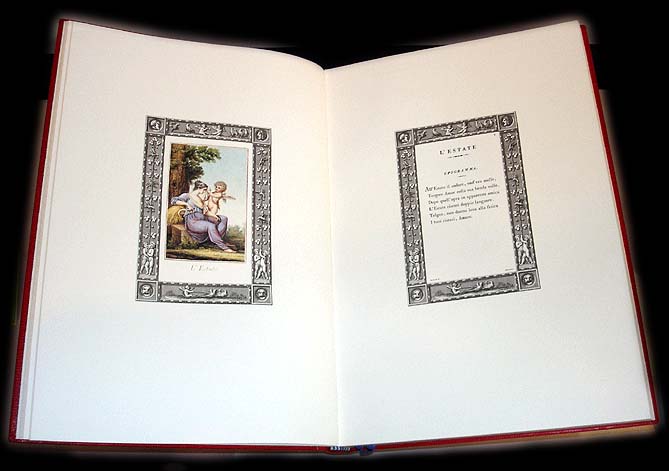
A letra neo-classicista de Bodoni
A mais «clássica» e pomposa letra de sempre — o excepcional desenho do mestre tipógrafo italiano. Os tipos Bodoni foram o resultado de 250 anos de evolução no design do tipo romano: linhas finas e subtis contrastam fortemente com hastes mais pesadas.
Os caractéres de Giambattista Bodoni também são determinados pelo seu forte acento vertical.
"Os caracteres criados por Bodoni caracterizam-se agora sobretudo pela passagem subtil e cuidadosamente estudada do traço fino ao traço grosso ou pela coexistência de hastes finas e grossas, num jogo de claro escuro que é também o jogo em que é baseada a página bodoniana.
Com uma alternância estudada do corpo da letra nas linhas dos títulos e um cuidado especial na escolha dos papeis e das tintas, a página é ampla, simples, com margens e espaçamentos entre linhas generosos e grandes áreas da página em branco.
A procura de clareza e luminosidade da página é reforçada pelo uso de tipos com altura-x reduzida e longos ascendentes e descendentes. Esta dialéctica do branco e negro dos caracteres é já, claramente, neo-clássica."
(Da apresentação de João Bicker à sua tradução do Manual Tipográfico de Giambattista Bodoni, Coimbra, Almedina, 2001, pg.38-39)
Torquato Tasso, Aminta, favola boschereccia, Parma 1789
As quatros fontes da beleza de um caractere, segundo Bodoni
«Dos quatro aspectos dos quais emana toda a beleza de um caractere, o primeiro é a regularidade. Analisando o alfabeto de qualquer idioma, vamos encontrar não só traços similares num grande número de letras distintas, mas também verificar que podem ser compostas de poucas partes idênticas, combinadas em grupos.
Se tomarmos a média de tudo – o que não serve para distinguir uma letra da outra –, e acentuarmos tão claramente quanto possível as dife­renças mais necessárias para esta distinção, conseguiremos fixar, para determinar a forma de todas as letras, uma ordem e uma regra; surge semelhança sem ambiguidade, variedade sem dissonância, igualdade e simetria sem confusão.
[...] Em segundo lugar vêm a nitidez e o polimento, oriundos da perfeição dos buris e da fundição perfeita dos caracteres. [...] A terceira condição é a escolha das melhores formas, em concordância com o bom gosto, com o espírito da nação e o espírito do século.
A moda reina na escrita como em todas as coisas, impon­do-lhe regras, razoáveis ou não. No entanto, se não houver nenhum motivo melhor e se a moda nos deixar livres, o bom gosto irá orientado pela simplicidade — não a simplicidade grosseira que se mani­festaria em traços uniformemente espessos, mas por uma simplicidade agradável e de boa qualidade, como a que observamos no harmonioso contraste de claro e escuro em todo a caligrafia feita com uma pena bem apontada e firme.
A graça é o quarto e último requisito para com­pletar a beleza do impresso. Sabemos quão difícil é explicar o que há de atraente, encantador e delicioso naquilo a que chamamos «graça». Mas como a graça deve sempre tender a parecer natural e inerente, deve fugir à afectação e ao esforçamento, a ponto de não estar errado procurá-la no que há de mais raro e mais perfeito, no que possa ser o cruzamento dum puro dom de Deus e de uma feliz natureza, embora ela geralmente não seja senão fruto de longos exercícios e do hábito, o qual torna tão fáceis as coisas mais difíceis que, mesmo sem pensar, as realizamos com perfeição.
Um caractere será pois tanto mais belo quanto mais tiver regularidade, nitidez, bom gosto e graça.»
Do Prefácio ao Manuale Tipografico, Parma, 1818.
Cimelio
Bodoni imprimiu Il Cimelio em 1811
Revivalismos da fonte de Bodoni
Em 1901, a fundição italiana Nebiolo remoldou o tipo Bodoni. Atualmente existem dezenas de redesenhos da Bodoni, baseados nas fontes publicadas no Manuale.
A versão existente na Adobe Type Library é proveniente da versão criada por Morris Fuller Benton para a Linotype entre 1908 e 1915.
• ATF Bodoni de M.F. Benton (1907-1915)
• Mergenthales Linotype Bodoni (1914-1916)
• Haas Bodoni (1924-1939)
• Bauer Bodoni de Louis Hoell (1924)
• Berthold Bodoni (1930)
A Bauer Bodoni é uma versão da Bodoni que foi criada em 1926 pelo tipógrafo Heinrich Jost (1889–1949), para a Bauer. Jost foi o director artístico da Fundição de tipos Bauer de 1822 até 1948.
Paginar com essa fonte exige atenção ao desenho vertical das letras e o forte contraste entre as linhas grossas e finas que podem afectar a legibilidade. Portanto é aconselhável usar a fonte em um corpo maior com um espacejamento generoso.
Bibliografia e publicações
Andreoti, Roberto. Parma dal 1768 al 1813. Bodoni celebrato a Parma. Biblioteca Palatina. Parma, 1963.
Benassi, Umberto. Il tipografo Giambattista Bodoni e i suoi allievi punzonisti. Archivio storico per le province parmensi, nuova serie, 13, pp. 3 — 115. Parma, 1913.
Blumenthal, Joseph. Art of the Printed Book, 1455 – 1955. New York, 1992.
Bodoni, Giambattista. Fregi e majuscole incise e fuse da Giambattista Bodoni. Parma, 1771. Fac-símile. Cambridge, 1982.
— Manuale tipografico. Parma, 1788. Fac-símile editado por Giovanni Mardersteig. Verona, 1968.
— Manuale tipografico. Parma, 1818. Fac-símile. London, 1960. Parma, 1965.
— G.B. Bodoni’s preface to the Manuale tipografico of 1818, now first translated into English with an introduction by H.V. Marrot. London, 1925. Reimpressão: London, 1953.
De Lama, Giuseppe. Vita del Cavaliere Giambattista Bodoni. Parma, 1816. Nova edição, ed. por Leonardo Farinelli e Corrado Mingardi. Parma, 1989.
Dwiggins, William Addison. Layout in Advertising. 1.ª edição: Harper and Brothers Publishers. New York, 1928. Edição revista: 1948.